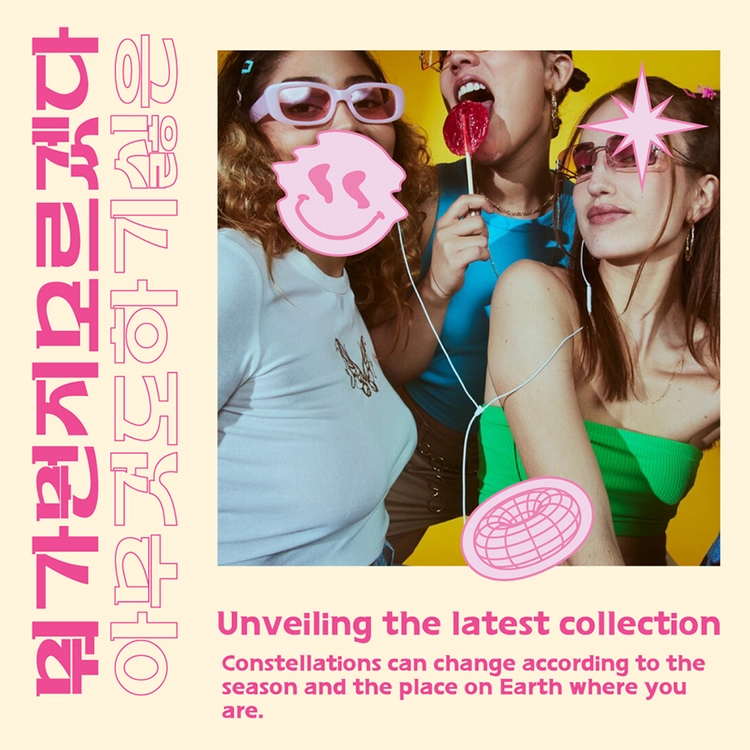
무려 9년 전에 네이버 오픈사전에 등재된 '긱시크'가 다시 유행하고 있습니다. 우리는 MZ세대가 애정한다는 긱시크의 특별한 감성을 폰트로 표현해보고 싶었습니다. 긱시크의 독창적인 개성을 담아, 다양한 창작물에 긱시크의 매력을 더할 것입니다. 긱시크MZ 폰트로 독특하고 대담한 스타일을 표현해 보세요!